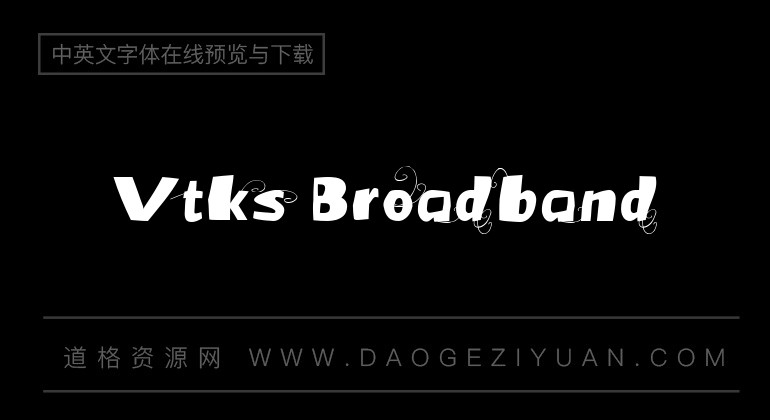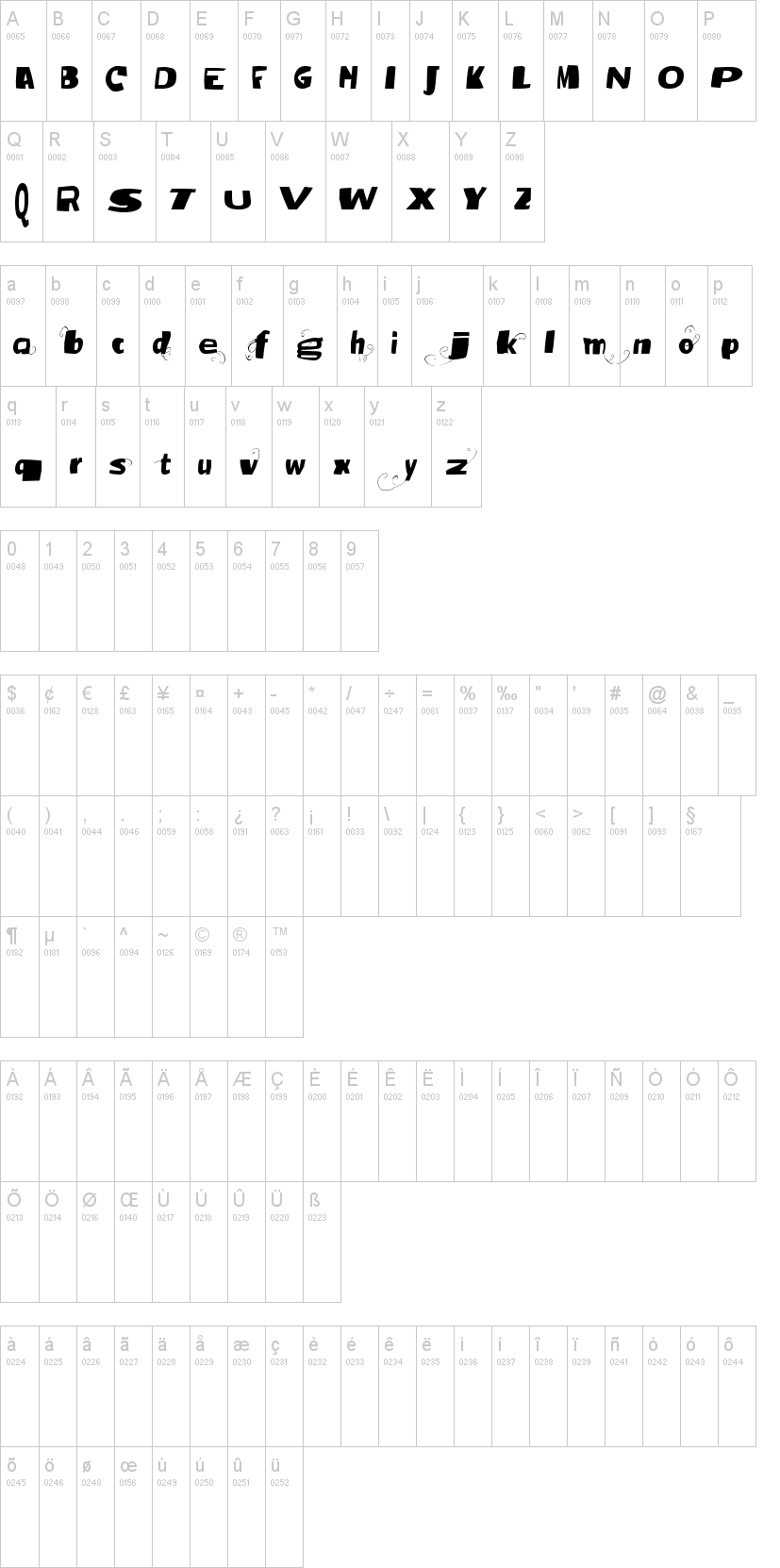
? Vtks Broadband 是一款粗体字体,由 Vtks Design 创作,它可以在大多数设计软件中使用,以及各种平台和媒体上使用。它具有突出的特色,能够提供清晰的视觉效果,并且在不同的尺寸和色彩下都可以保持其突出的视觉效果。它的字形设计也很独特,拥有较宽的字母,更加明显的粗细,以及精确的线条。它可以用于标题,抬头,标签,广告,海报,网站等等。内容介绍
Vtks Broadband是一款非常不错的手写艺术字体,具有很好的视觉感,适合于文化类的宣传设计、商业类品牌的广告和产品包装设计以及个性化文字排版等较多场景。